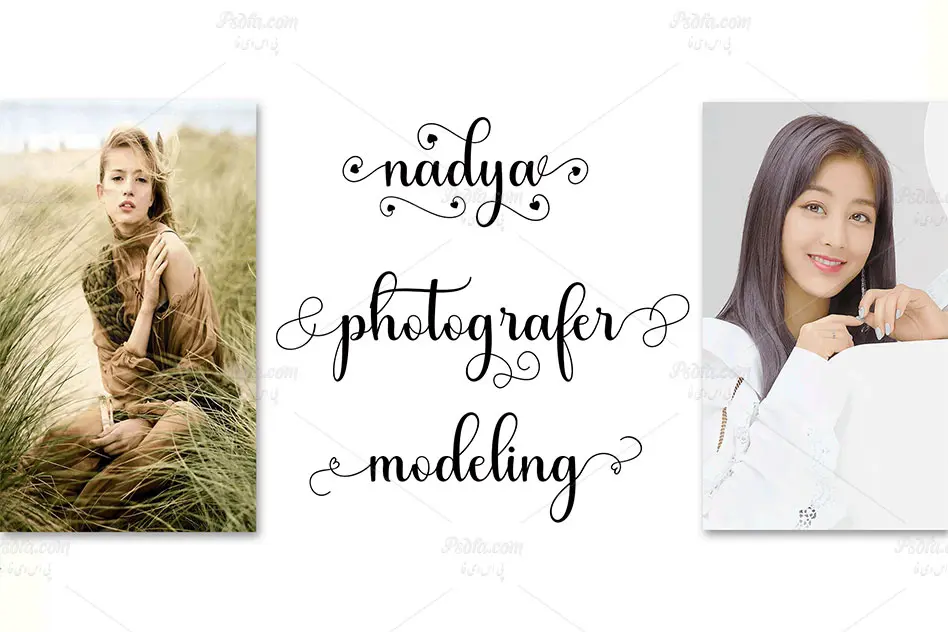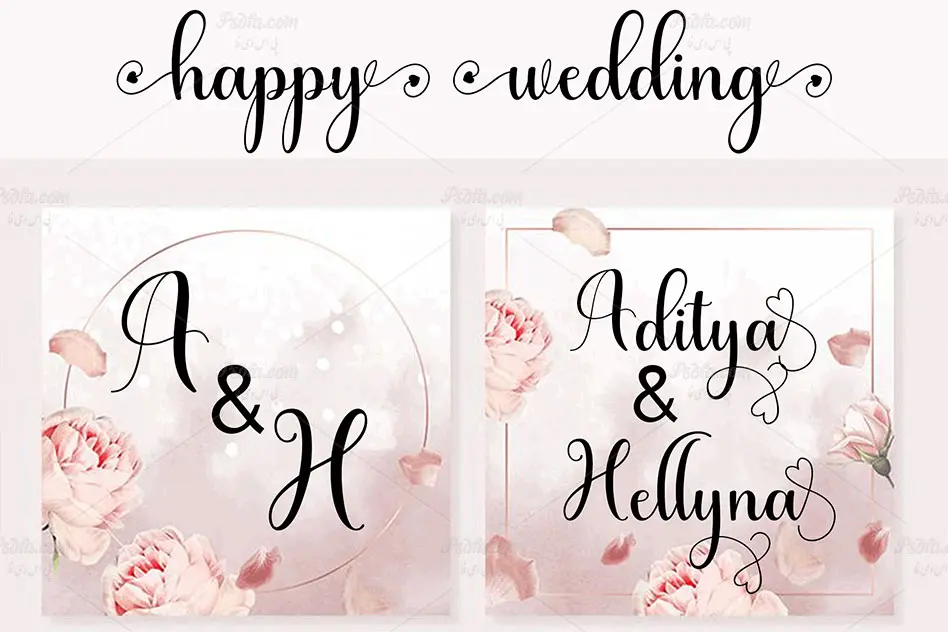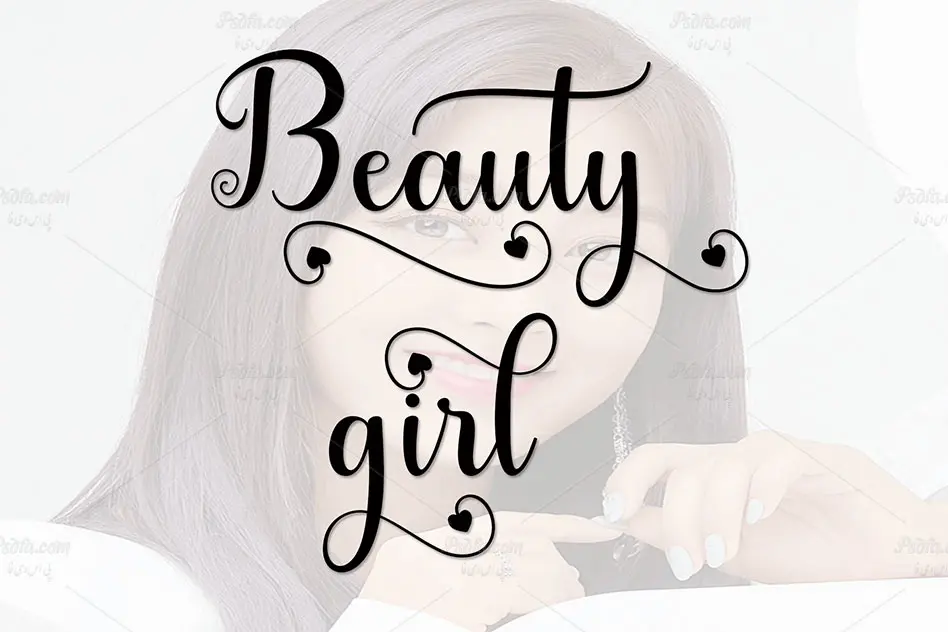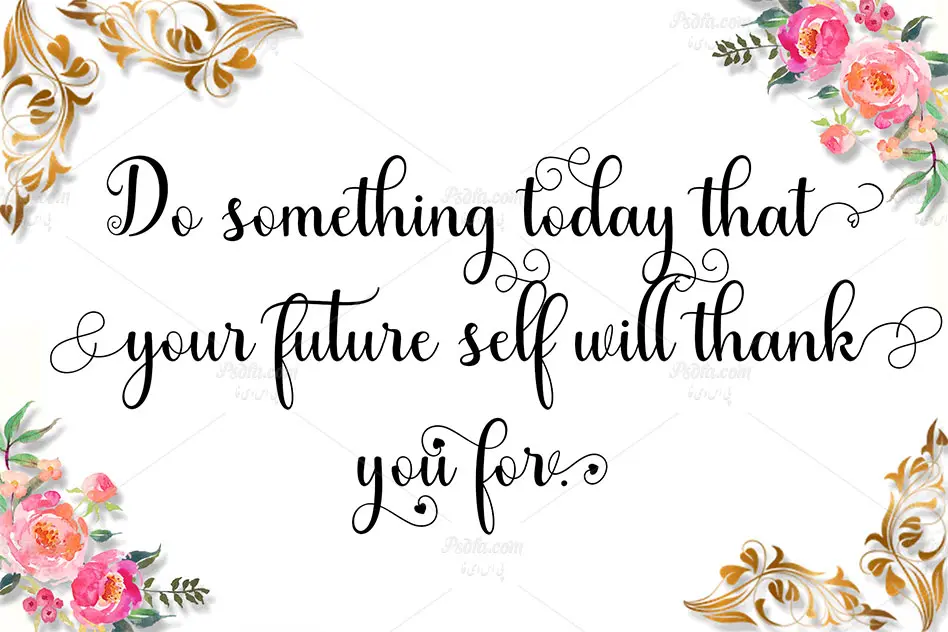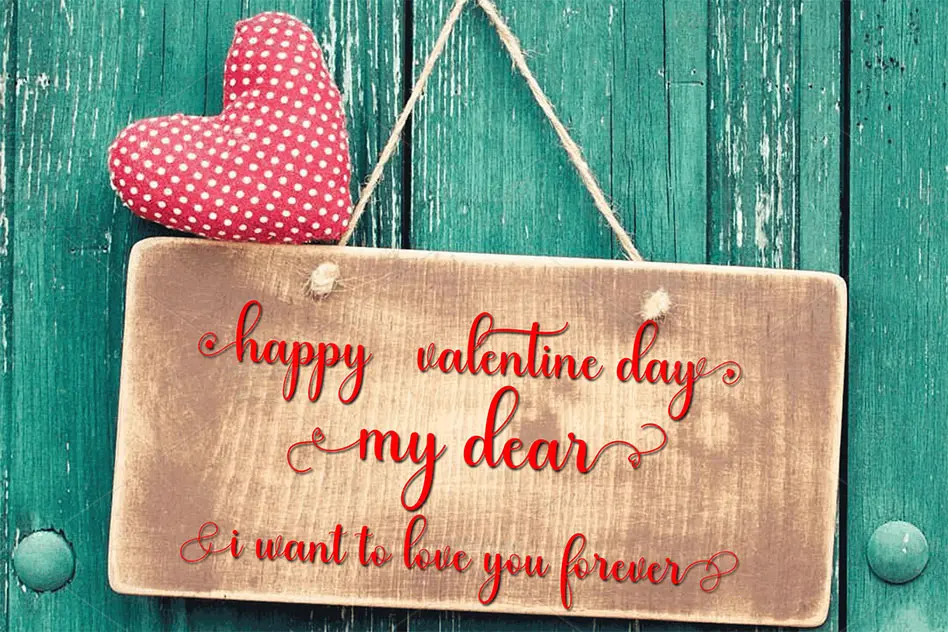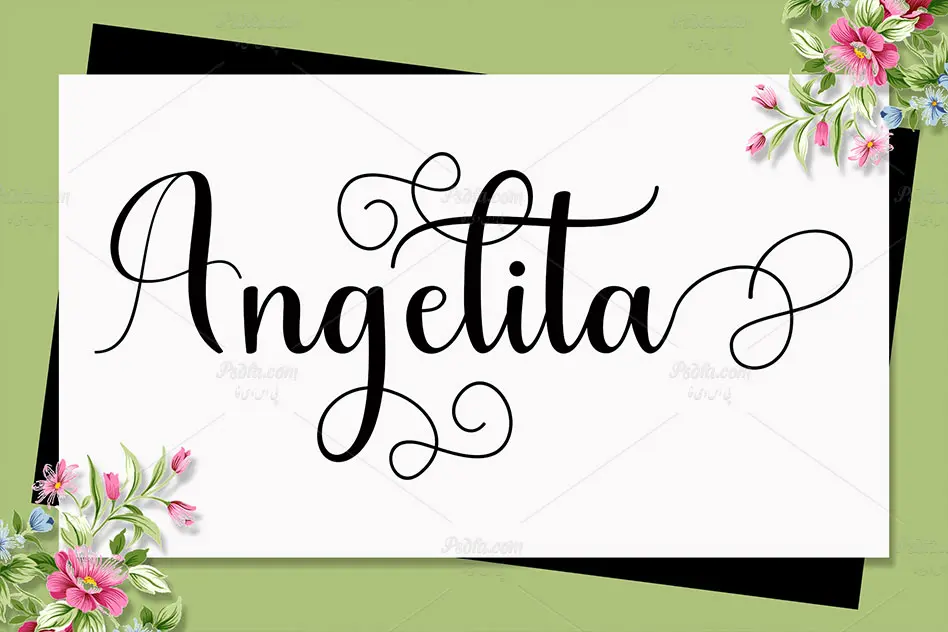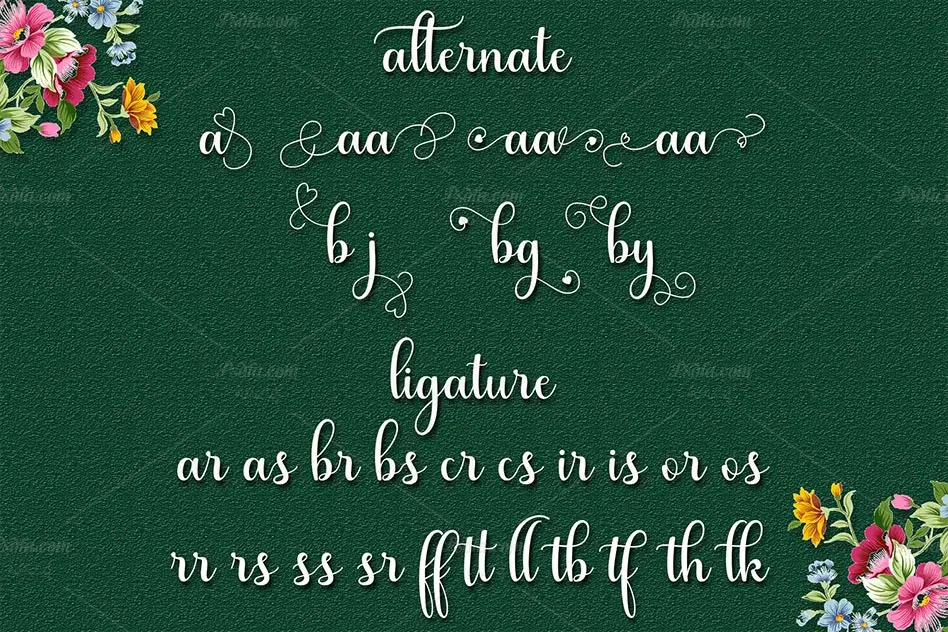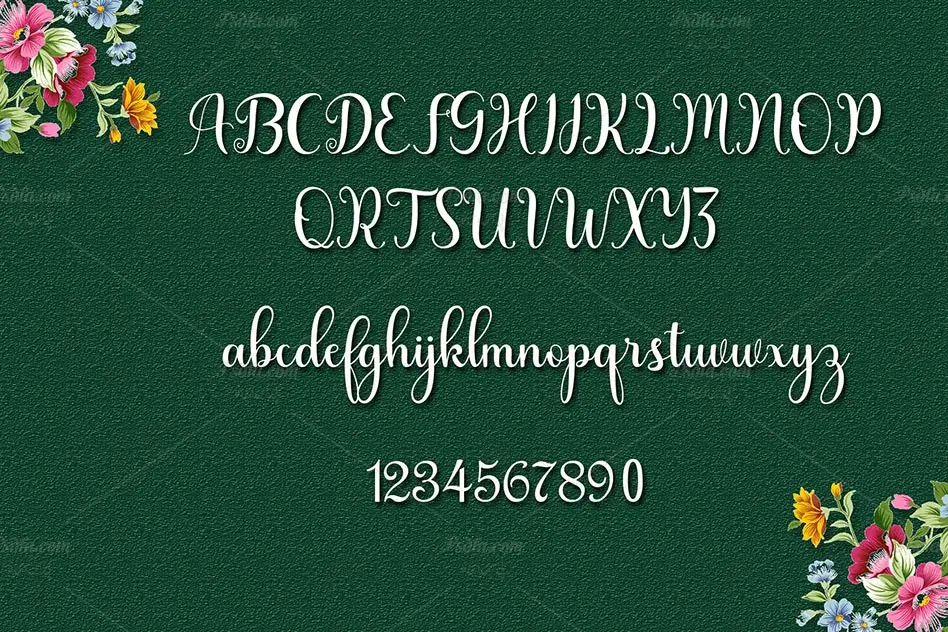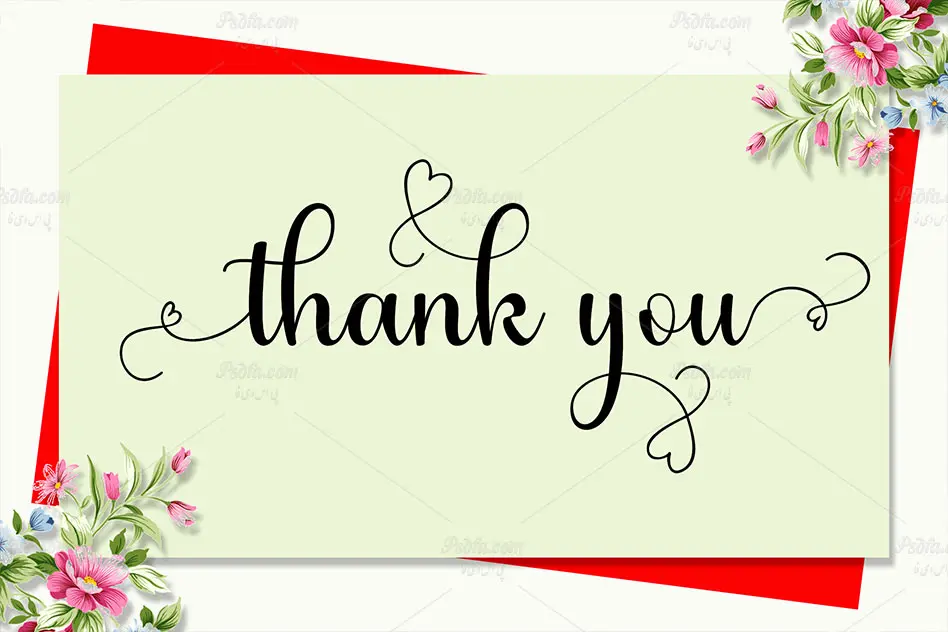
فونت انگلیسی رمانتیک و عاشقانه جولیا که در این مطلب شاهد آن هستید یک فونت دستنویس فوق العاده زیبا است که میتوان از آن در طرحهای گرافیکی به خصوص طراحی انواع کارت تبریک، کارت پستال و کارت عروسی استفاده نمود. این فونت زیبا در قالب 2 فایل ttf, otf بر روی سایت بارگذاری شده است که با نصب یکی از این دو فرمت در پوشه فونتهای سیستم، قادر به استفاده از آن در تمام نرمافزارهای گرافیکی و ویرایشگر متن از جمله نرمافزار فتوشاپ، افترافکت، مجموعه نرمافزار آفیس و … خواهید بودو فونت Julayha در وزن معمولی (Regular) طراحی شده است که از آن میتوانید در طرح و پروژههای گرافیکی خود استفاده کنید.
- نام فونت : Julayha
- وزن : معمولی (Regular)